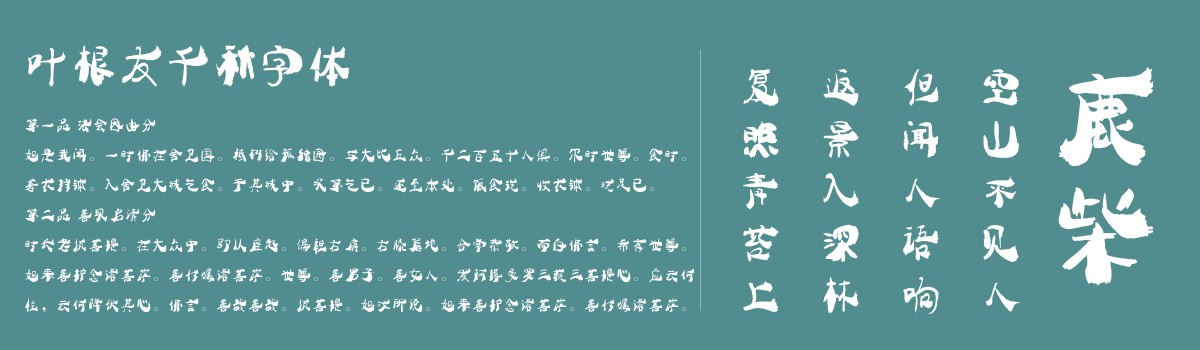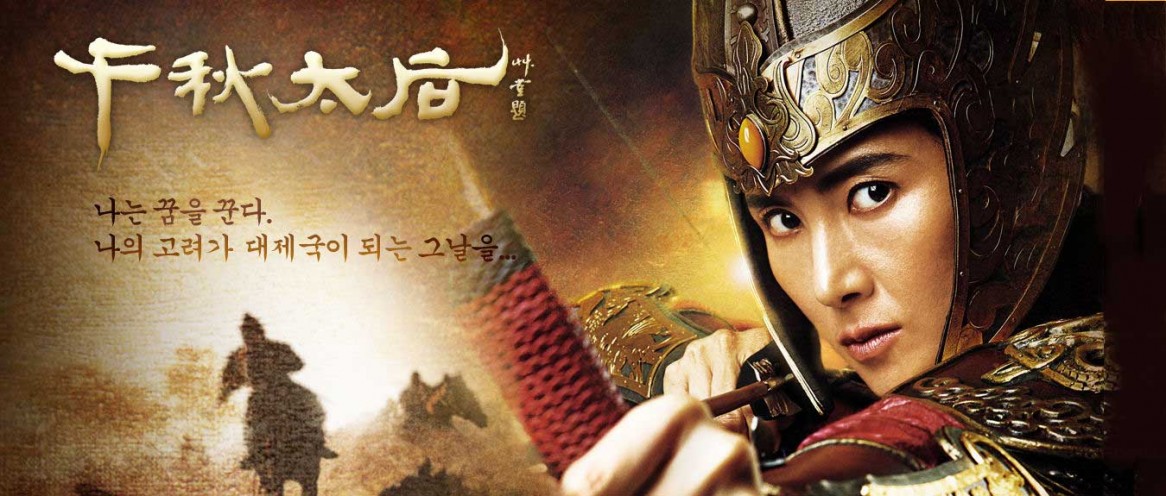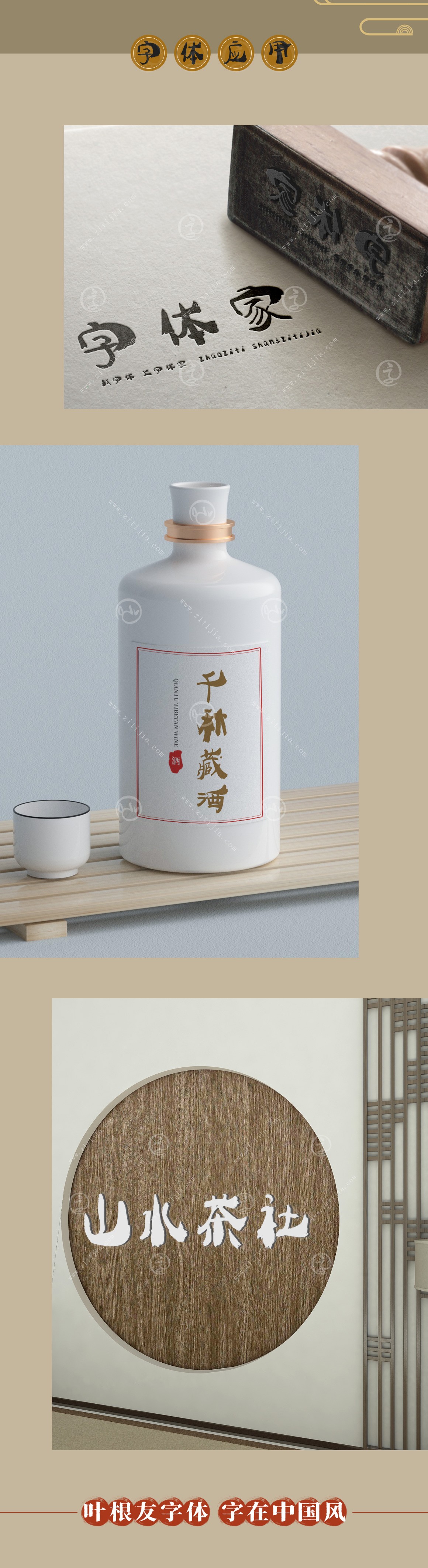
叶根友千秋字体
字体作者:叶根友
创作年代:2013年
字体字数:6763个中文汉字以及其他英文字母和阿拉伯数字
字体介绍
叶根友千秋字体风格浑厚大气,延续隶书的风格特征进行创作,灵感来自韩国电视剧《千秋太后》之剧名书法“后”的风格,经过创意改变思维模式,创新了一款叶根友千秋字体作品,这个字体的风格特征是每个字的笔画尾部都上扬,浑厚而富有书法韵味,浓重之中展现了中国书法抑扬顿挫之运笔追求,是继蚕燕隶书之后又一毛笔隶书作品的发布。
创意来源